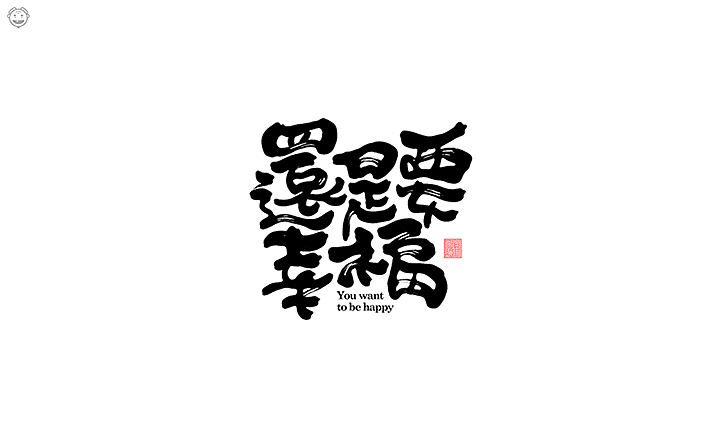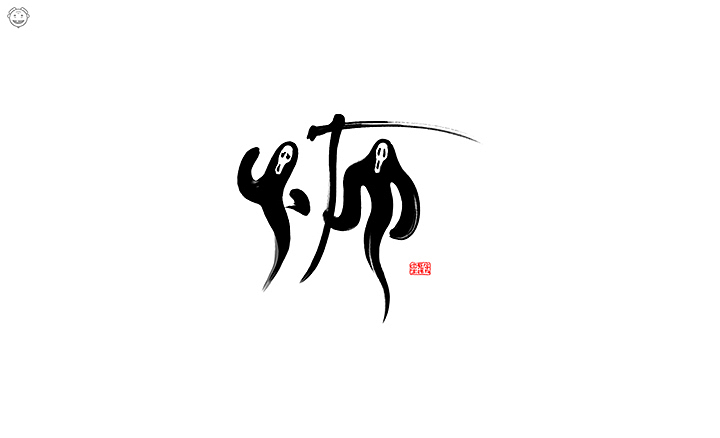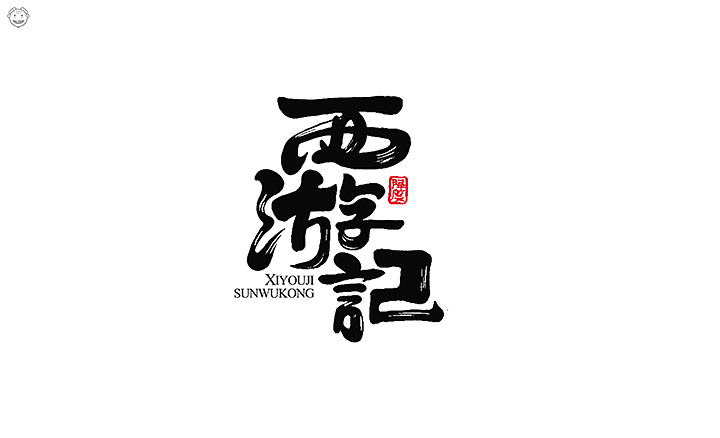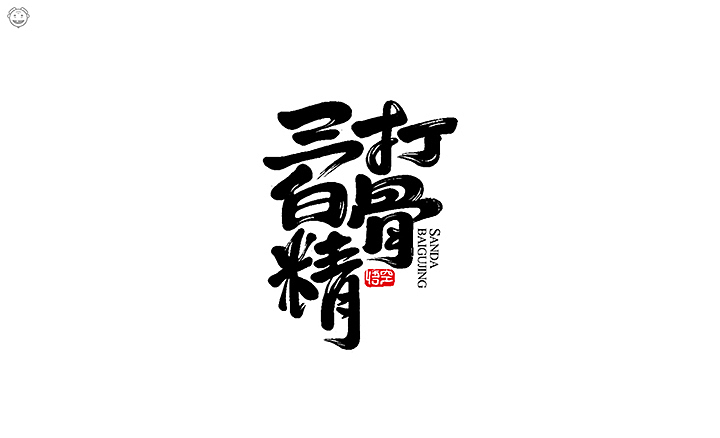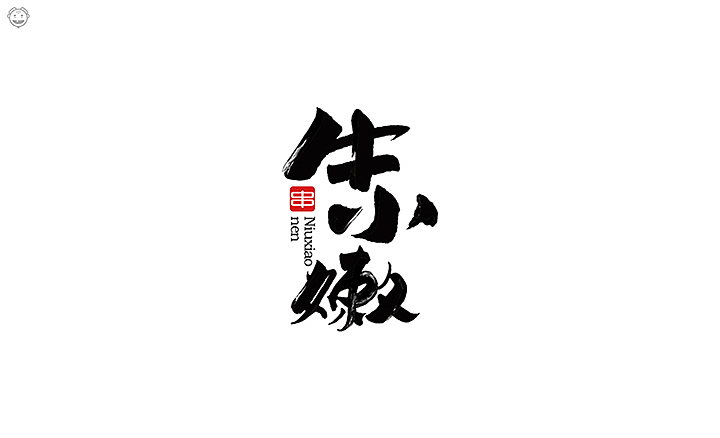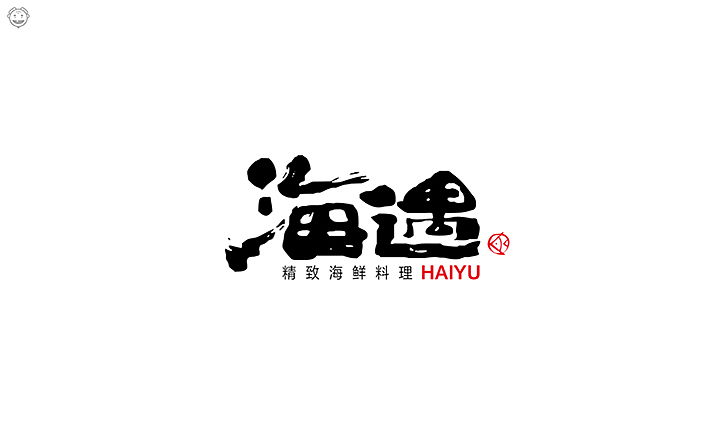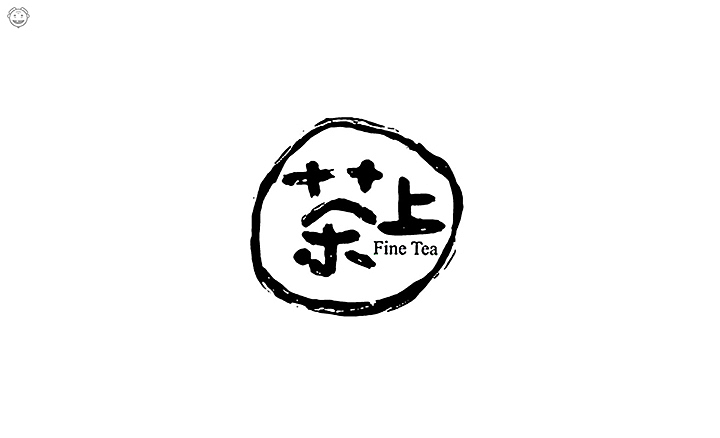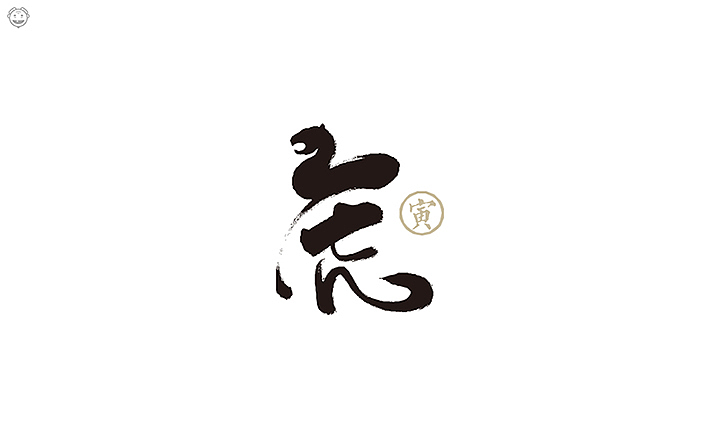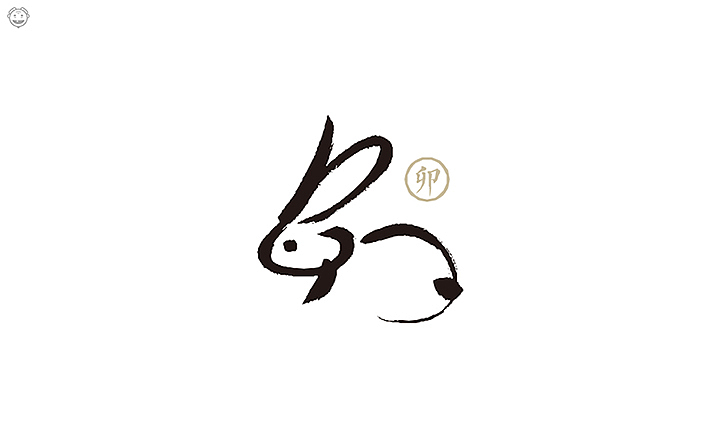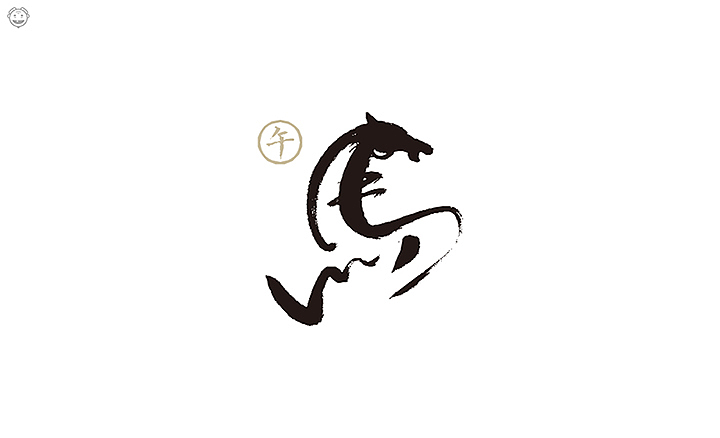
近期书法类字体小集
有一段时间没发字体作品了,今天整理了一下,不怎么全!但还算丰富!大部分都是ipad或者手绘板写的!不能说是书法吧,叫“毛笔写的美术字”比较贴切!哈哈!看看吧!风格多样,希望对大家有帮助!
无蔗糖谐音
为北京华狮品牌成立14周年酒会而写
所有人的追求吧!
还是要幸福,有时只是幻想!
这个人好多人不认识!你认识吗?
做了一个西游的梦,梦见我和悟空喝酒!然后醒来写了三组西游主题!
象形12生肖,有字、有图!
这个我很喜欢!
ipad写的,用在包装上!
首都后面的一棵树,卖的是昌平苹果!
九叠篆《千字文》局部
左手反写的字,是不是挺有感觉?下图是写字时候的帅帅的样子!
看到谷字的玄机了吗?是一个跪拜的老人!
这个老板说,两年开店200家,送我一辆前途跑车!
三组清酒风的字,随便写着玩的,是不是很有感觉?